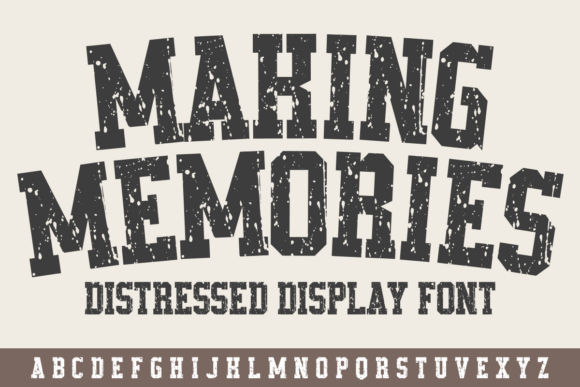
Making Memories
Making Memories – A Fonte que Transforma Cada Projeto em História
Se você procura uma tipografia que una força, nostalgia e um toque de tradição esportiva, a Making Memories chega como a escolha perfeita. Desenvolvida com um visual “varsity” desgastado, esta fonte display traz a sensação de décadas de vitórias, ideal para quem deseja comunicar orgulho universitário, marca esportiva ou pôster vintage.
Características que Fazem a Diferença
• Estilo Distressed: Textura realista que simula anos de uso, proporcionando um aspecto autêntico e “guerreiro”.
• Conjunto Completo de Maiúsculas: Perfeita para headlines de alto impacto, monogramas e logos que precisam transmitir autoridade.
• Aplicações Ideais: Camisetas universitárias, uniformes esportivos, pôsteres de viagem retro, projetos DIY, SVGs e muito mais.
Por que a Making Memories é a Melhor Opção para Seu Projeto?
• Visual robusto e reconhecível: As letras grossas e texturizadas garantem legibilidade mesmo à distância, essencial para camisetas, bandeiras e sinalização de eventos.
• Apelo emocional: O aspecto “vintage” evoca memórias de conquistas passadas, conectando seu público a uma sensação de tradição e orgulho.
Em resumo, a Making Memories não é apenas uma fonte – é uma ferramenta de storytelling visual que acrescenta peso, caráter e história a qualquer criação. Experimente agora e veja seus projetos ganharem vida com a energia dos campeões!